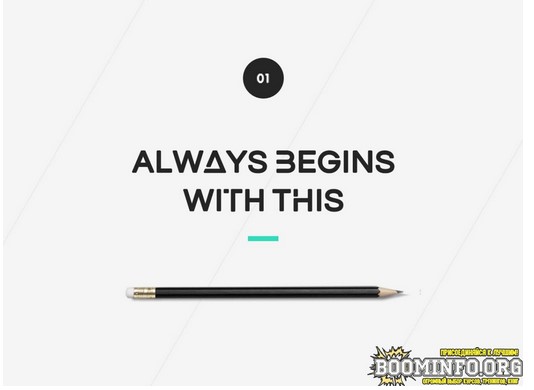
[UI8] Gaoel - Soft, bold & elegant all caps typeface (2021)
Gaoel - это новый шрифт со всеми прописными буквами, который кажется каким-то знакомым. Он унаследовал честный тон, который является уверенным, но не высокомерным, уютным, но не мягким, гладким, но не шатким. В результате получился гибрид, сочетающий гуманистические пропорции и несколько геометрический вид. Он идеально подходит для оформления заголовков, визуальной идентификации брендинга, редакционных статей, плакатов и т.д. Gaoel включает два стиля.
Выделения
2 стиля прописных букв
Цифры
Пунктуация
Акценты (многоязычные символы)